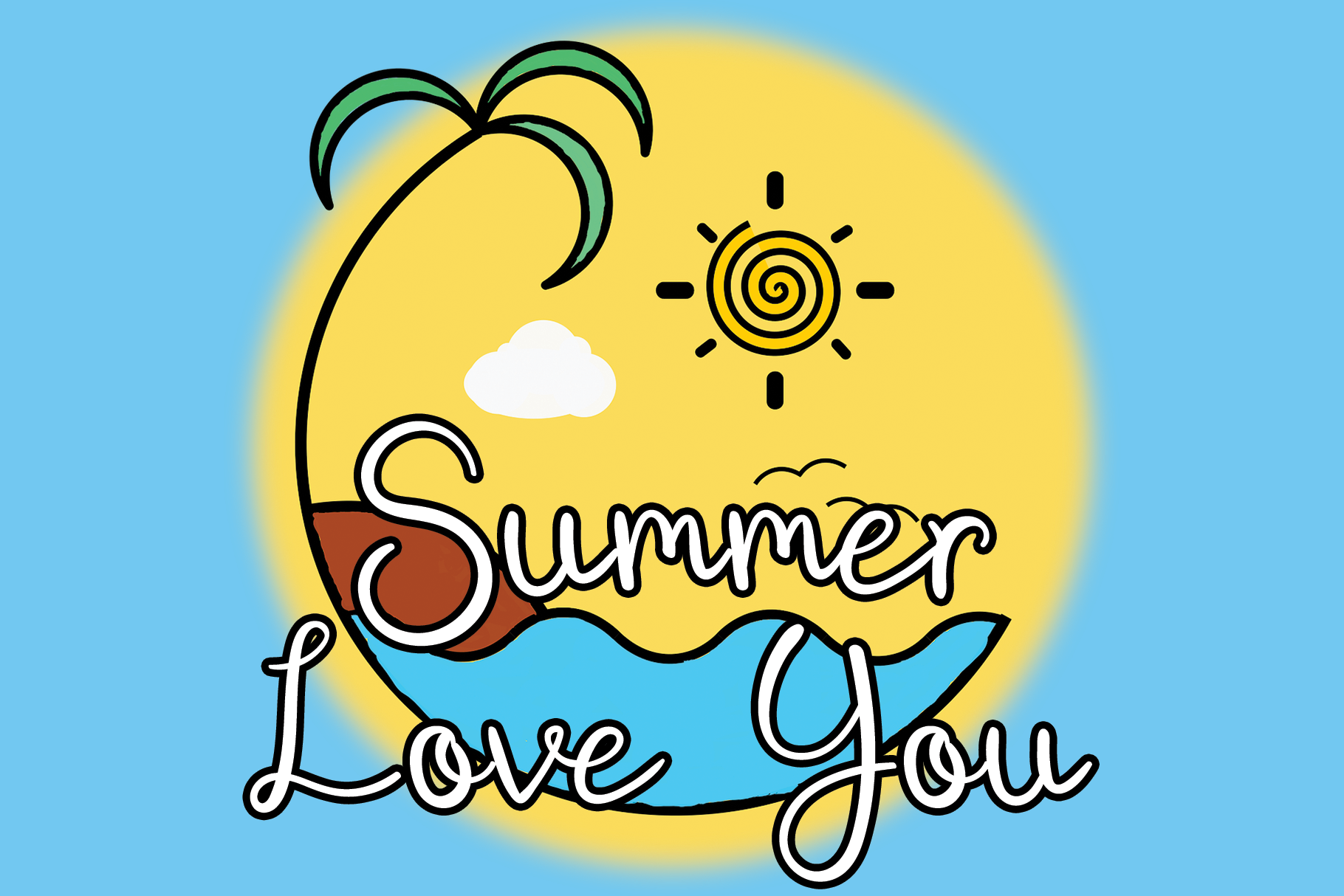
Summer Love You Font – Download Grátis
Esta é uma fonte escrita à mão cuidadosamente criada pelo designer el hotcig, com um toque elegante. Ela é ideal tanto para ideias criativas que você deseja transformar em uma postagem no Instagram como para projetos de arte DIY que exigem scripts de letra aquarela. Seja você um artista digital ou amantes do scrapbooking, este fonte Summer Lovely You trará uma pitada mágica e elegância aos seus trabalhos. Não apenas é perfeita para escrever mensagens pessoais com carinho, ela também enriquece qualquer projeto que a use, tornando-o único e impecável. Seja sua próxima ideia de arte digital ou seu próximo trabalho de DIY de scrapbooking — esta fonte terá uma sensação mágica para transformá-lo em algo especial.